Читаемость числовых данных: нули, разделители и знаки
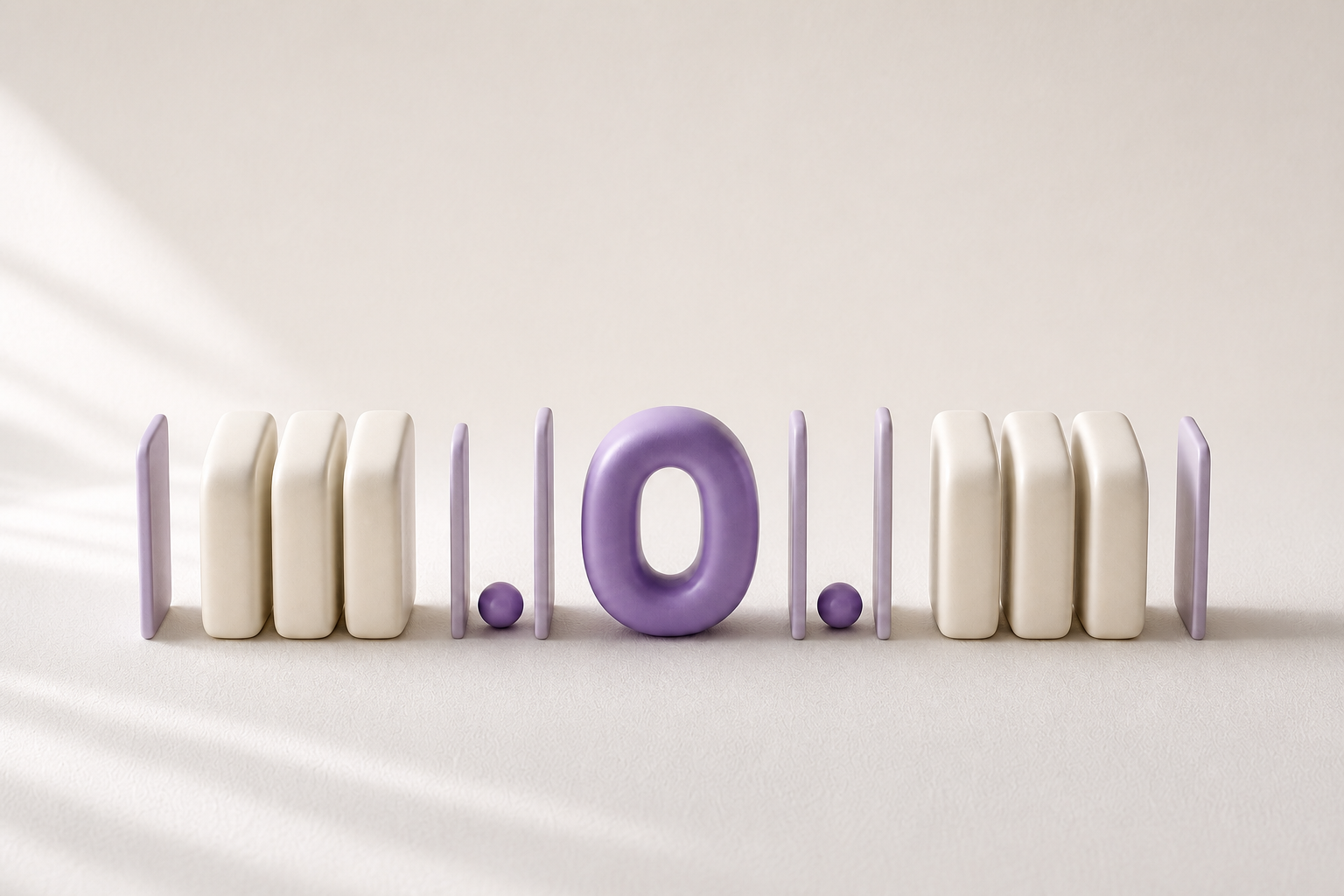
Читаемость числовых данных зависит не только от размера цифр, но и от того, как оформлены нули, пробелы, разделители тысяч и десятичные знаки. Последовательная запись помогает быстро сравнивать значения, не путать порядок величин и замечать ошибки. В статье разберём типографические правила, выбор шрифта и практические примеры для интерфейсов, таблиц и документов.
Почему числам нужна отдельная типографика
Число читается как структура: человек мгновенно оценивает количество разрядов, положение десятичного знака, единицы измерения и знак перед значением. Если элементы оформлены непоследовательно, взгляд вынужден каждый раз заново разбирать запись. Ошибка в одной цифре, потерянный ноль или незаметная запятая могут изменить смысл суммы, процента, координаты или показателя.
Хорошая числовая типографика снижает когнитивную нагрузку. Группировка разрядов помогает читать длинные значения, одинаковая ширина цифр упрощает сравнение в столбцах, а правильные интервалы отделяют число от его единицы измерения. Поэтому оформление числовых данных следует проектировать так же внимательно, как иерархию заголовков, подписи кнопок и основной текст.
Нули показывают точность и масштаб
Ноль в числовой записи не является пустым местом. Он может обозначать отсутствие величины, сохранять разряд или показывать точность измерения. В записи 0,75 ноль перед запятой помогает сразу увидеть, что значение меньше единицы. В записи 12,50 два знака после запятой могут сообщать о формате данных или требуемой точности, даже если математически число равно 12,5.
Ведущие нули перед десятичной частью
Для дробных значений меньше единицы используйте ноль перед десятичным знаком: 0,5, 0,08, 0,125. Запись ,5 визуально менее устойчива: знак может потеряться в узком интерфейсе, таблице или при переносе строки. В финансовых, технических и медицинских документах ведущий ноль особенно важен, потому что он однозначно обозначает масштаб значения.
Конечные нули и заявленная точность
Конечный ноль после десятичного знака стоит сохранять, если он является частью принятого формата: 4,20 руб., 7,00 %, 2,50 м. Однако в обычном описательном тексте лишние нули могут утяжелять запись. Выбирайте одно правило для всего набора данных: например, всегда показывать два знака в ценах и не показывать незначащие нули в кратком пояснении.
Разделитель тысяч помогает читать большие числа
Длинные числа лучше группировать по три цифры, считая от десятичного знака влево: 1 000, 12 500, 1 250 000. В русскоязычном наборе для такого разделения обычно используют пробел, а не точку и не запятую. Пробел делает границы разрядов заметными и не конкурирует с десятичной запятой, поэтому запись 1 234 567,89 читается однозначно.
Для чисел, которые могут переноситься на новую строку, нужен неразрывный пробел между группами разрядов. В визуальном редакторе важно проверить, что пробел не исчезает при копировании, а в интерфейсе — что число не распадается на отдельные фрагменты. Если техническая система не поддерживает такую настройку, лучше предусмотреть более широкую колонку или уменьшить размер числа, а не удалять разделители.
Когда разделитель тысяч не нужен
В коротких числах до четырёх цифр разделитель часто не добавляет пользы: 2026 год, 1200 пикселей, 1500 рублей. Но если рядом стоят более крупные значения, единый формат может улучшить сравнение: 1 200, 12 000 и 120 000. Для дат, артикулов, кодов и идентификаторов группировку нельзя вводить механически, если она меняет привычный формат или мешает копированию.
Десятичная запятая или точка: выбирайте по контексту
В русскоязычных текстах десятичным разделителем обычно служит запятая: 3,14; 0,75; 12,5 %. Точка встречается в программном коде, некоторых международных стандартах, технических системах и данных, предназначенных для машинной обработки. Главное требование — не смешивать варианты в одном документе, таблице или экране без явного объяснения.
Если продукт рассчитан на несколько языков, формат чисел должен зависеть от локали пользователя. В русской локали интерфейс может показывать 1 234,56, а в англоязычной — 1,234.56. Это не декоративная деталь: разделитель меняет интерпретацию числа. Данные, которые передаются между системами, следует хранить в стабильном машинном формате, а отображать с учётом языка и региональных настроек.
Пробелы рядом с процентами, валютой и единицами
Число и его обозначение образуют смысловую пару, но не всегда должны слипаться. В русской типографике между числом и символом процента обычно ставят пробел: 15 %. Аналогично оформляются многие единицы измерения: 12 кг, 3,5 м, 20 °C. Для денежных значений важно выбрать один формат: 1 500 ₽, 1 500 руб. или 1 500 рублей — и применять его последовательно.
Читаемость числовых данных строится на последовательности: ноль перед дробью, понятная группировка разрядов, единый десятичный знак, аккуратные пробелы и подходящая ширина цифр. Эти решения помогают быстрее сравнивать значения и уменьшают вероятность ошибки в тексте, интерфейсе или таблице.